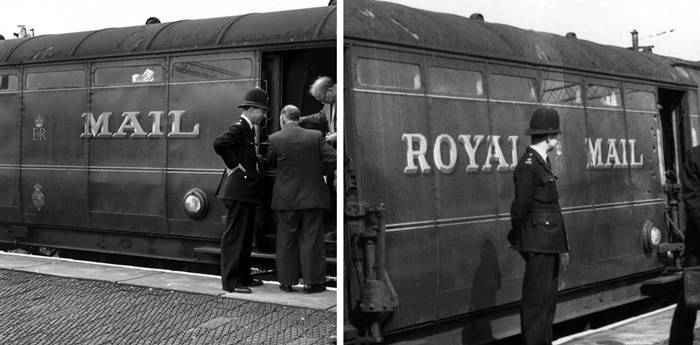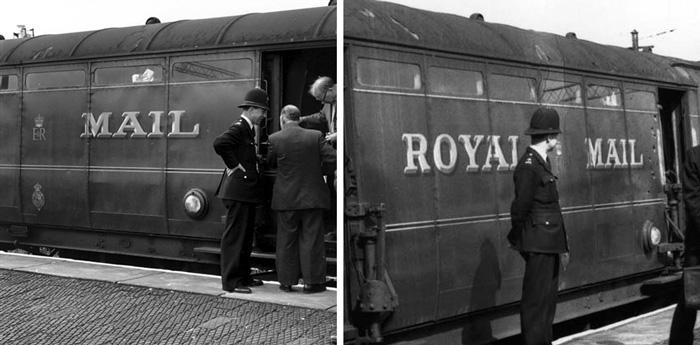
Alte Schift der Royal Mail
Ich suche die Schrift die die Royal Mail auf diesem Zug verwendet hat.
Ich habe jetzt schon länger gesucht und nur in SlabSerif Schriften- wie der
Rockwell oder Memphis- so ein A gefunden mit Serifen oben.
Für gemalte Schriften gab es Vorlagen. Kann gut sein, dass du diese in irgendeinen der vielen Copybooks for Writing Masters, Lettering Artists usw. findest.     Wenn es im Display-Schriften wie diese geht, waren die Autoren der Copybooks die Schrifthersteller meistens etwas im voraus. Kann auch sein, dass die Royal Mail eigene Musterzeichnungen hatte, die immer noch unbemerkt in irgendein Archiv schlummern.
Zu der Schriftart:
Die Serifen der Beschriftungen der Royal Mail sind viel dünner als die einer klassischen Egyptienne. Schriften wie Rockwell und Memphis scheiden damit aus, die Stärke der Serifen ähnelt eher die einer Clarendon.